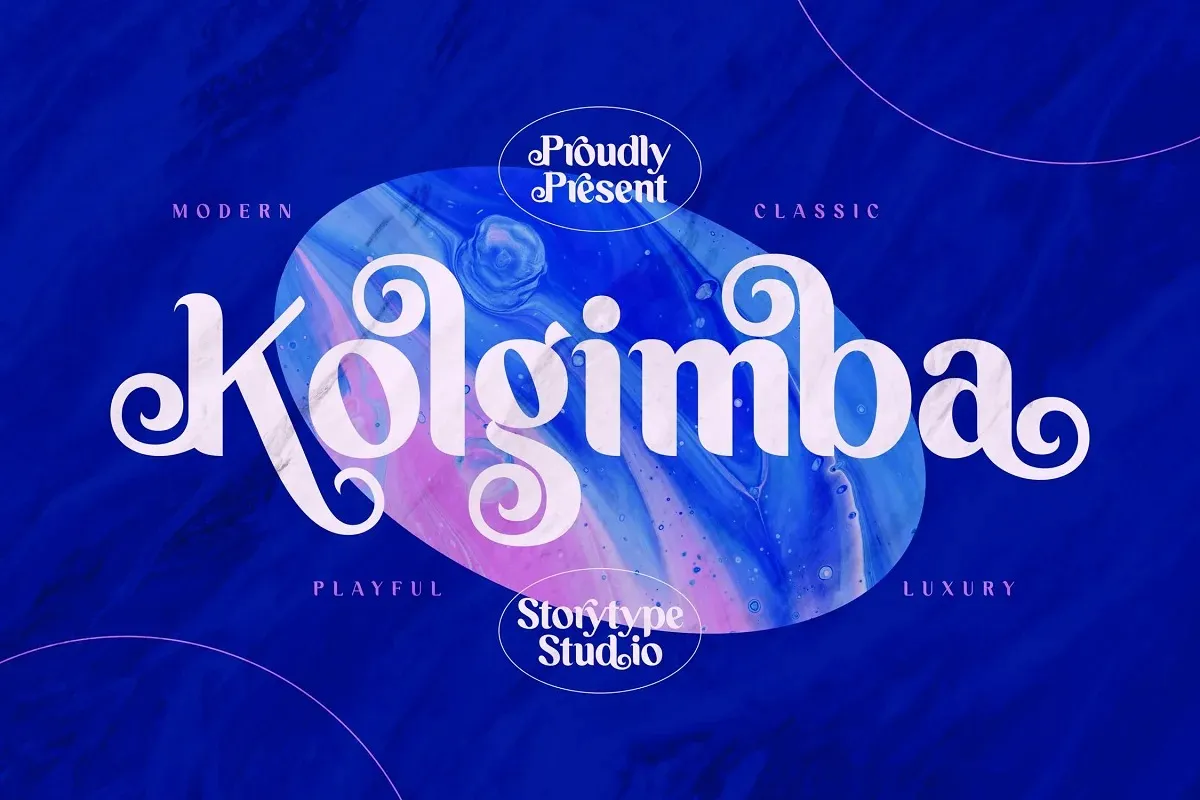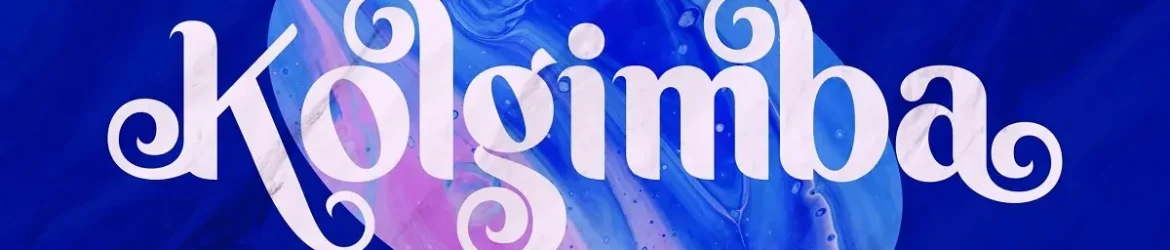
A fonte ‘Kolgimba’ é uma tipografia sans serif que combina elegância com modernidade. Com ligaturas alternativas especiais e grafos complementares únicos, ela oferece uma ampla gama de possibilidades para designers, ideal para estilos sofisticados e luxuosos como logotipos de marcas de luxo, títulos de livros ou filmes, marcas de moda, magazines fashion, letras ilustrativas e até mesmo citações. Seja em seu design gráfico mais elaborado ou simplificado, ‘Kolgimba’ está à sua disposição para transformar seus projetos de maneira única e atraente. A fonte traz um toque moderno às suas criações, garantindo que ela atenda todas as necessidades de designers na categoria de sans serif.